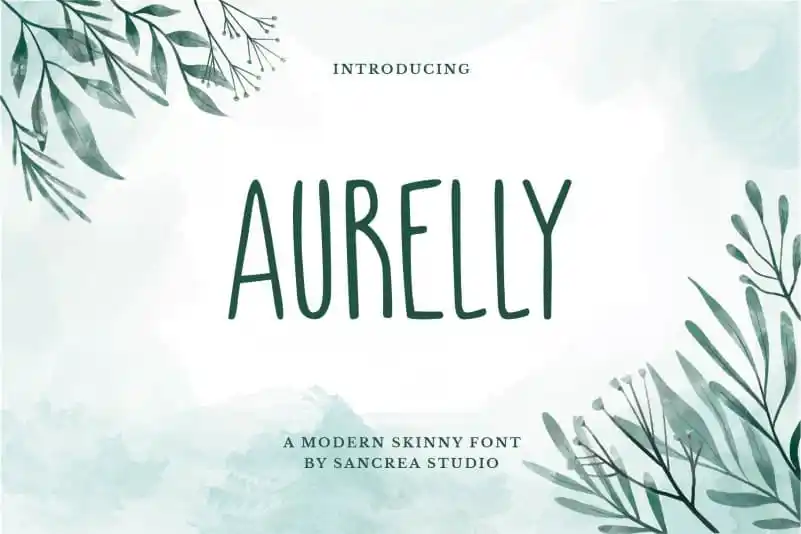
Aurelly Display Font – Download Grátis
Aurelly Display Font é uma elegante fonte sans-serif que se inspira na escrita manuscrita apertada, fornecendo um toque alegre e moderno para cartões de visita, logotipos, declarações de texto e convites. Com sua tipografia esguia, você pode adicionar uma característica única que destaca seu design em diferentes ambientes. Especialmente adequado para marcas, embalagens, anúncios, casamentos e fotografias, Aurelly Display é perfeitamente complementada por outras fontes, tornando-a uma escolha valiosa para qualquer projeto que valorize o toque humano de uma escrita manuscrita. Esta fonte idealmente combina a simplicidade do sans-serif com a personalização única da escrita livre, criando um contraste perfeito entre funcionalidade e estética pessoal.